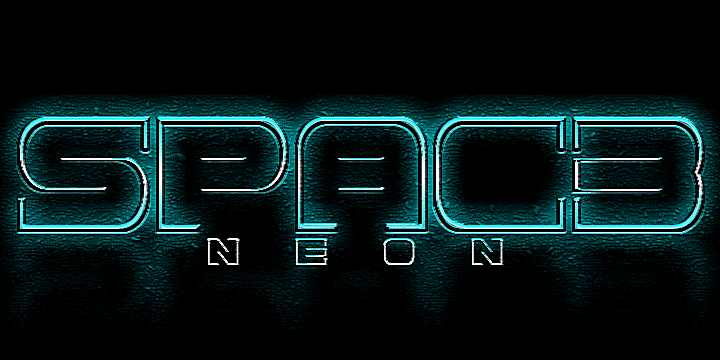
Spac3 neon font – Fonte Grátis
Spac3 neon font
Descubra a fonte Spac3 Neon para sua próxima obra! Esta elegante e moderna fonte sans-serif é perfeita para criar uma atmosfera envolvente e natural no seu design gráfico. Desenvolvida pelo designer Hamilton, essa fonte é ideal para projetos que exigem um estilo clean e minimalista. O Spac3 Neon traz linhas retas, formas limpas e tonalidades sóbrias que se adaptam perfeitamente a uma variedade de aplicações, desde design gráfico até editoração digital. Sujeitável à adaptação rápida, essa fonte é adequada para uso em sites, redes sociais e aplicativos digitais. Com sua versão disponível em dois formatos (TTF e OTF), o Spac3 Neon pode ser facilmente integrado em seu trabalho sem a necessidade de licenças adicionais. Para obter mais informações ou pedir a versão completa, consulte o site http://qbotype.xunem.com/spac3neon/download.htm. Certifique-se de verificar os termos de uso antes de fazer qualquer download para garantir que você está respeitando as diretrizes de seu designer. Estamos aqui para ajudá-lo a alcançar novos níveis de criatividade, então se tem alguma dúvida ou precisar de mais informações sobre como usar o Spac3 Neon, estou à disposição. Aqui está uma fonte que vai deixar sua marca no design digital.